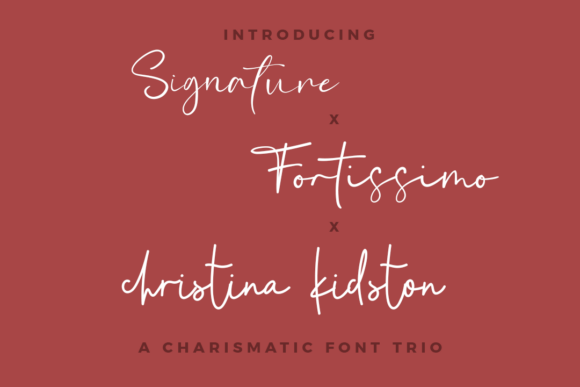
Signature Fortissimo Christina Trio
Signature Fortissimo Christina Trio gibi yüksek kaliteli varlıklar arıyorsanız, bu premium paket yaratıcı projeleriniz için harika bir seçimdir.
Hassasiyetle hazırlanan Signature Fortissimo Christina Trio, temiz vektörler, pürüzsüz tipografi ve içinizin rahat etmesi için ticari bir lisans sağlar.
İster İsteğe Bağlı Baskı (POD) ürünleri, ister düğün davetiyeleri veya sosyal medya grafikleri oluşturuyor olun, Signature Fortissimo Christina Trio ideal bir uyumdur.